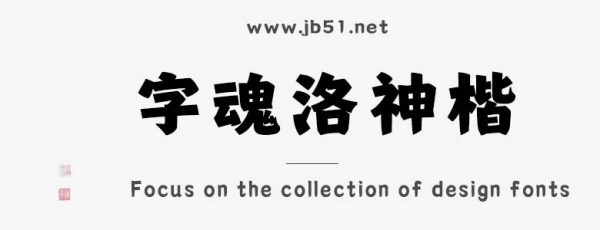
字魂洛神楷字體是由字魂字庫推出的毛筆書法字體,該字體包含7144個(gè)中文、字母、 符號(hào)和數(shù)字,具有中國風(fēng)的風(fēng)格,適合應(yīng)用于藝術(shù)設(shè)計(jì)、平面宣傳設(shè)計(jì)、網(wǎng)頁設(shè)計(jì),書法字帖等領(lǐng)域。
字魂洛神楷字體是一款商用的楷體,創(chuàng)意字體,該字體包含7144個(gè)中文、字母、 符號(hào)和數(shù)字,具有中國風(fēng)的風(fēng)格,可以滿足您設(shè)計(jì)上的各種需求,該字體主要用于黨政公務(wù)等場景, 您不但可以在字魂網(wǎng)下載字魂洛神楷字體,同時(shí)還有眾多毛筆書法字體、創(chuàng)意字體等可供選擇!